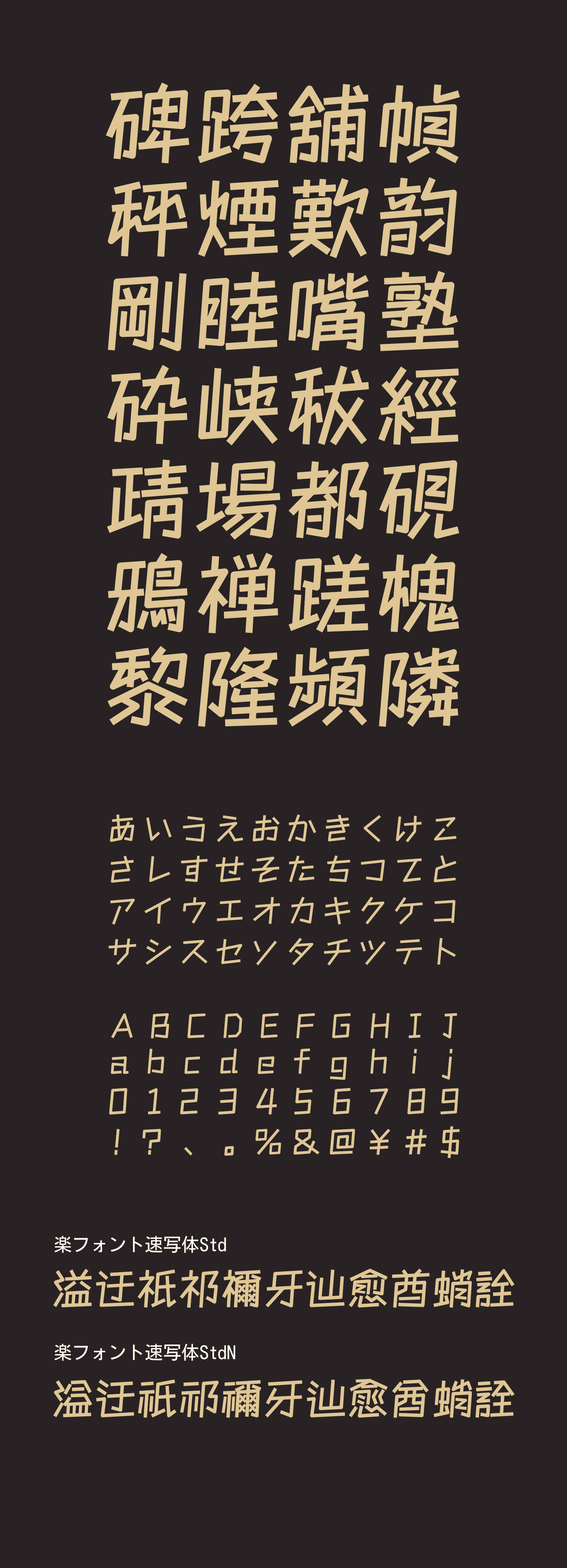
速写体(そくしゃたい)
文字の結び目は優雅で、ストロークの先端と末端の変化は安定感を求める、滑らかで力強く美しいリズム感に満ちる書体です。斜体のデザインにより文字の印象はエレガントで、美しい現代的な感じを与えます。 新聞や雑誌、書籍やポスター、メディアコミュニケーション、プロモーションなどに幅広く使用できます